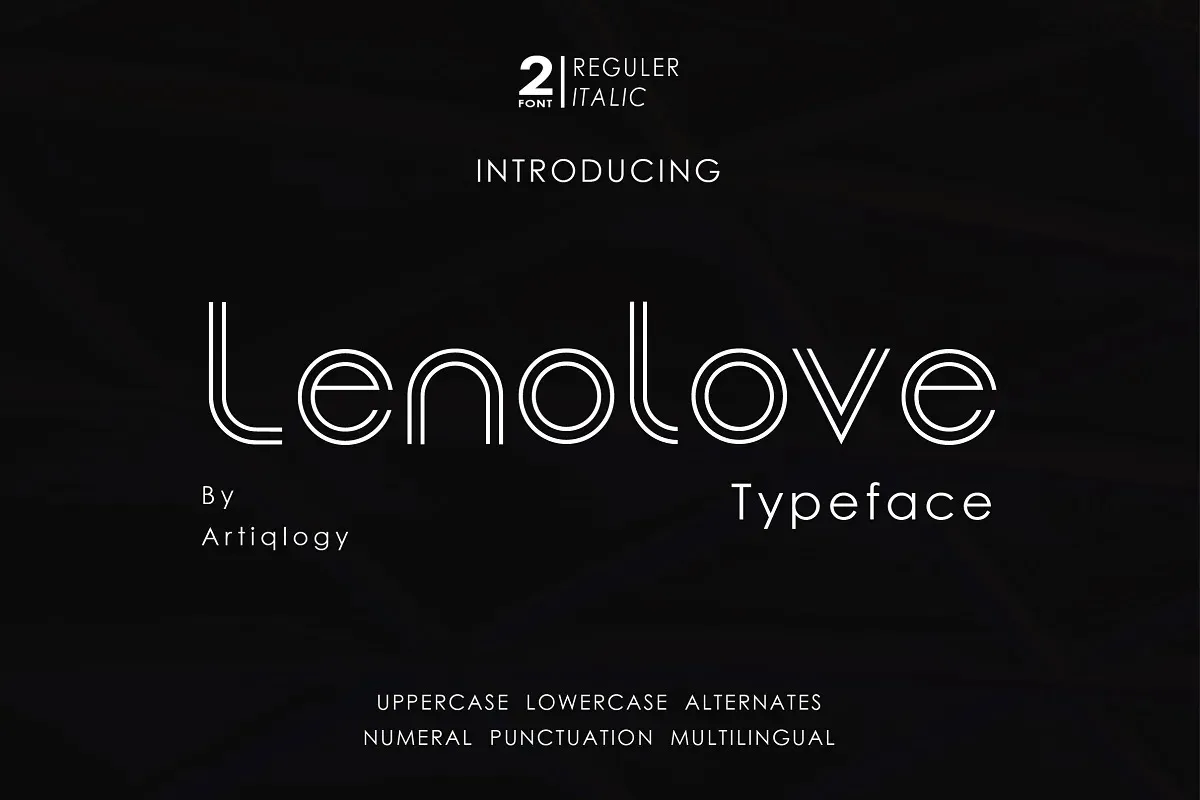
Lenolove Font – Download Grátis
A Lenolove Font é uma elegante tipografia de exibição ideal para projetos multi-funcionais que valorizam simplicidade e minimalismo. Desenvolvida pelo designer Artiqlogy, essa fonte se destaca pela sua simplicidade geométrica, característica marcante da família do tipo, mas também apresenta uma leve influência futurista e sci-fi. Com um forte foco em limpeza e clareza, a Lenolove é perfeita para adicionar um toque moderno ao seu design. Sua tipografia de exibição permite que ela seja usada de diversas maneiras – de logotipos impactantes a fontes de conteúdo profissional. Com sua riqueza geométrica e ar de futuro, a Lenolove se torna um recurso versátil e poderoso para designers e criativos em busca de uma adorável combinação de simplicidade e modernismo.